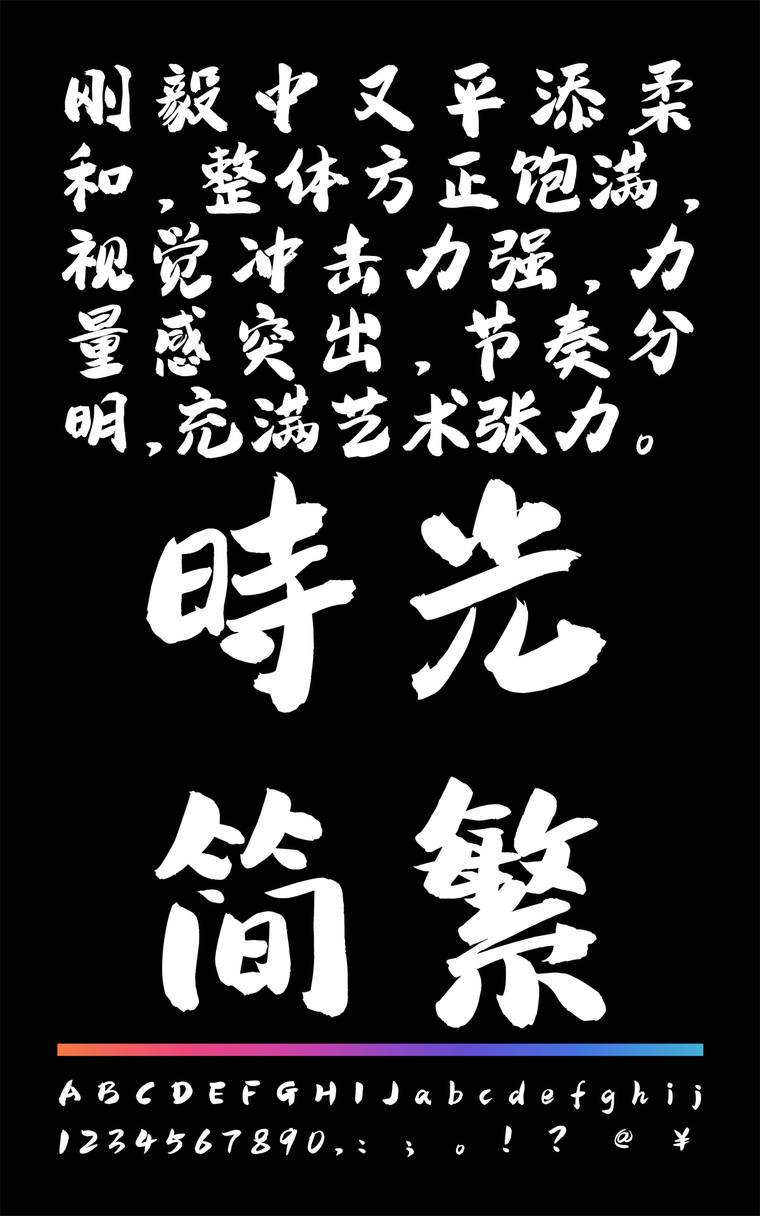
潮字社时光简繁
潮字社时光简繁,这款字体结构工整、笔画清晰,兼顾美观与易读性,适用于标题、正文、海报、包装、LOGO 等多种场景。字形优雅稳定,风格百搭耐看,适配日常排版与创意设计,让文字呈现更舒适、更具质感。潮字社时光简繁一笔一画,皆是细节,以均衡的比例、流畅的线条打造舒适视觉体验,字形端正大气,风格简约现代。无论是商业设计、品牌宣传还是日常排版,都能轻松驾驭,让文字更有格调与力量。潮字社时光简繁字体下载。
字体特征:潮字社时光体刚毅中又平添柔和,整体方正饱满,视觉冲击力强,力量感突出,节奏分明,充满艺术张力。